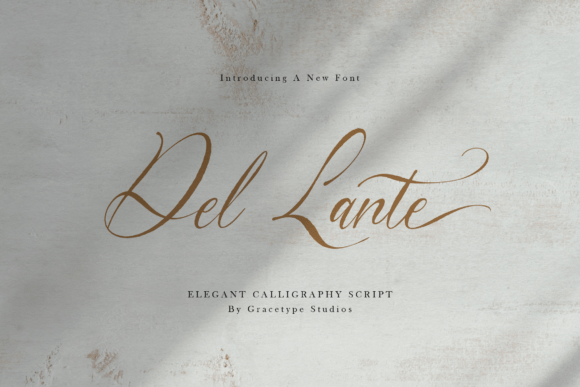
Del Lante
Del Lante – Elegância Caligráfica em Cada Traço
Del Lante é a personificação da graça caligráfica. Seus ascendentes amplos e swashes delicados criam um fluxo visual que parece dançar sobre a página. Essa fonte foi desenvolvida para momentos que exigem luxo e romance, tornando‑se a escolha definitiva para todo tipo de papelaria nupcial.
Por que Del Lante se destaca?
- Design fluido e romântico: laços intrincados e detalhes finos que evocam sofisticação artesanal.
- Versatilidade de aplicação: perfeita para convites de casamento, save‑the‑date, cartões de lugar e até mesmo marcas de alta joalheria ou perfume.
- Impacto visual em grandes formatos: em tamanhos maiores, os traços revelam elegância que pode ser potencializada com foil dourado ou texturas de letterpress.
Melhores usos para Del Lante
Quando você precisa que seu texto “sussurre” beleza, atemporalidade e artesanato, Del Lante entrega exatamente isso. Veja alguns cenários onde a fonte brilha:
- Convites de casamento e cartões de agradecimento – cria um convite que já transmite emoção antes mesmo de ser aberto.
- Branding de joias de luxo – as linhas delicadas reforçam a exclusividade da marca.
- Embalagens de perfume – o toque etéreo combina com fragrâncias sofisticadas.
- Marca‑da‑água de fotografias artísticas – acrescenta um ar de elegância sem sobrepor a imagem.
- Materiais de marketing premium – folhetos, catálogos e banners que merecem um visual refinado.
Conclusão – Vale a pena investir?
Se o seu projeto requer uma tipografia que una luxo, romance e artesanato, Del Lante é a escolha certeira. Seu design fluido, a presença de caracteres PUA e a capacidade de ser realçado com técnicas de impressão de alto padrão garantem que sua comunicação visual nunca passe despercebida. Não perca a chance de transformar simples palavras em verdadeiras obras‑de‑arte.